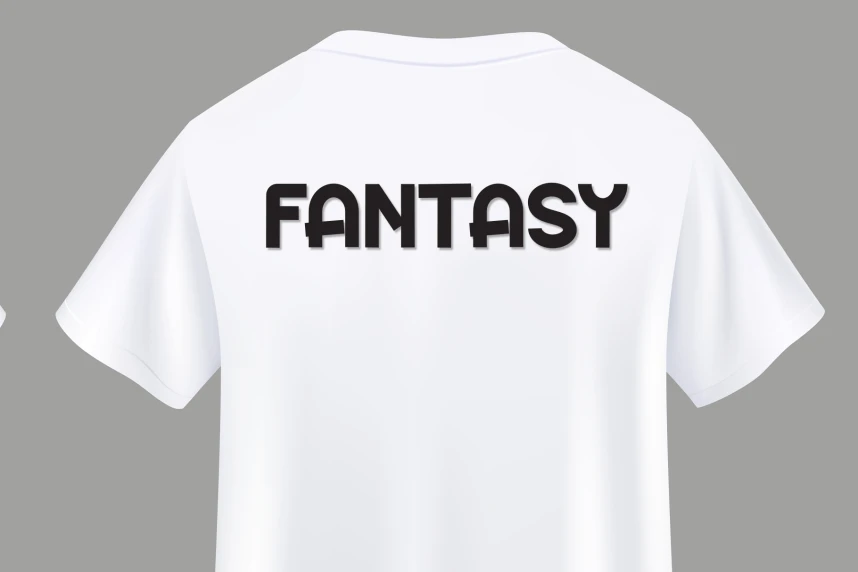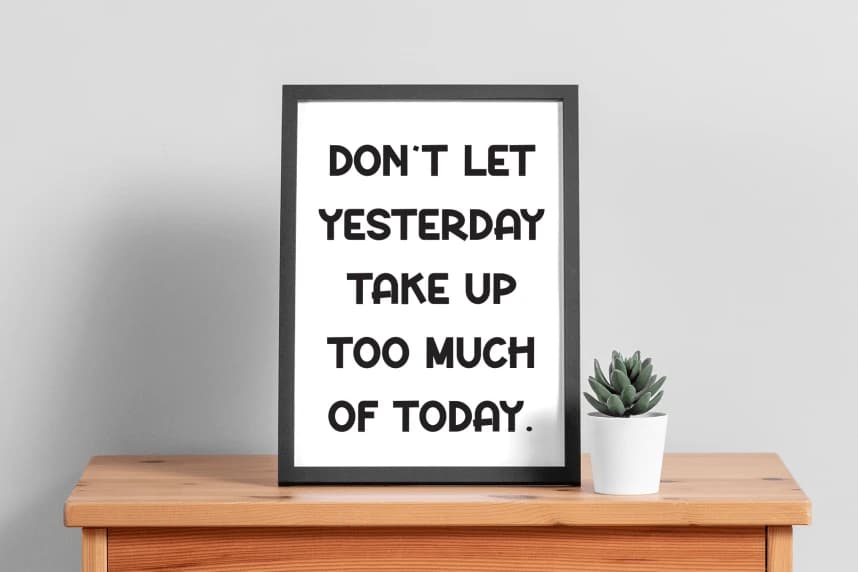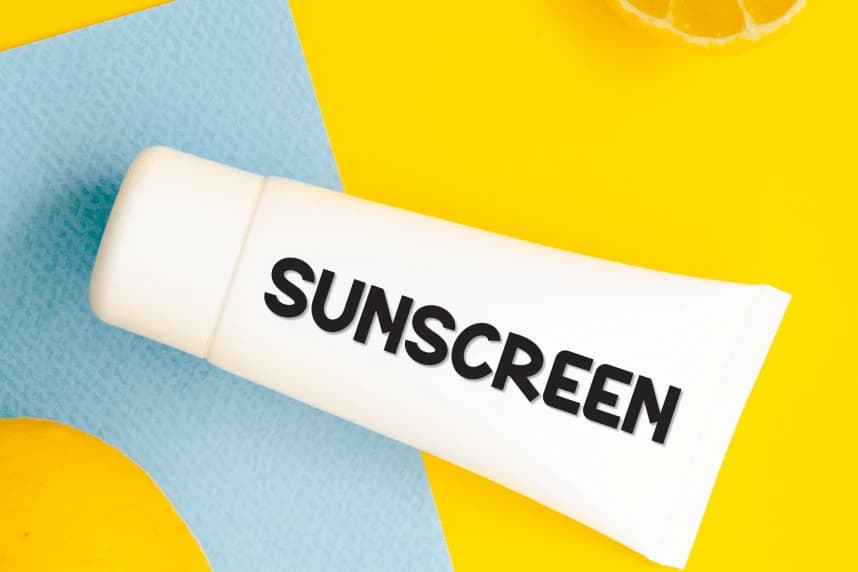
Sabah Öğretmen Oyunbaz Yazı Tipi
Morning Teacher Playful Font, tatlı ve samimi bir el yazısı gösterim yazı tipidir. Sevimli ve eğlenceli olan bu yazı tipi, düğün davetiyelerini yazmak, kartlar oluşturmak veya herhangi bir tasarımda eğlenceli bir dokunuşa ihtiyaç duyduğunuz her durumda idealdir!
Morning Teacher Playful Font, tatlı ve arkadaş canlısı bir el yazısı gösterim yazı tipidir. Sevimli ve eğlenceli olan bu yazı tipi, düğün davetiyelerini, kartları veya oyunbaz bir dokunuşa ihtiyaç duyabilecek herhangi bir tasarımı yazmak için idealdir!